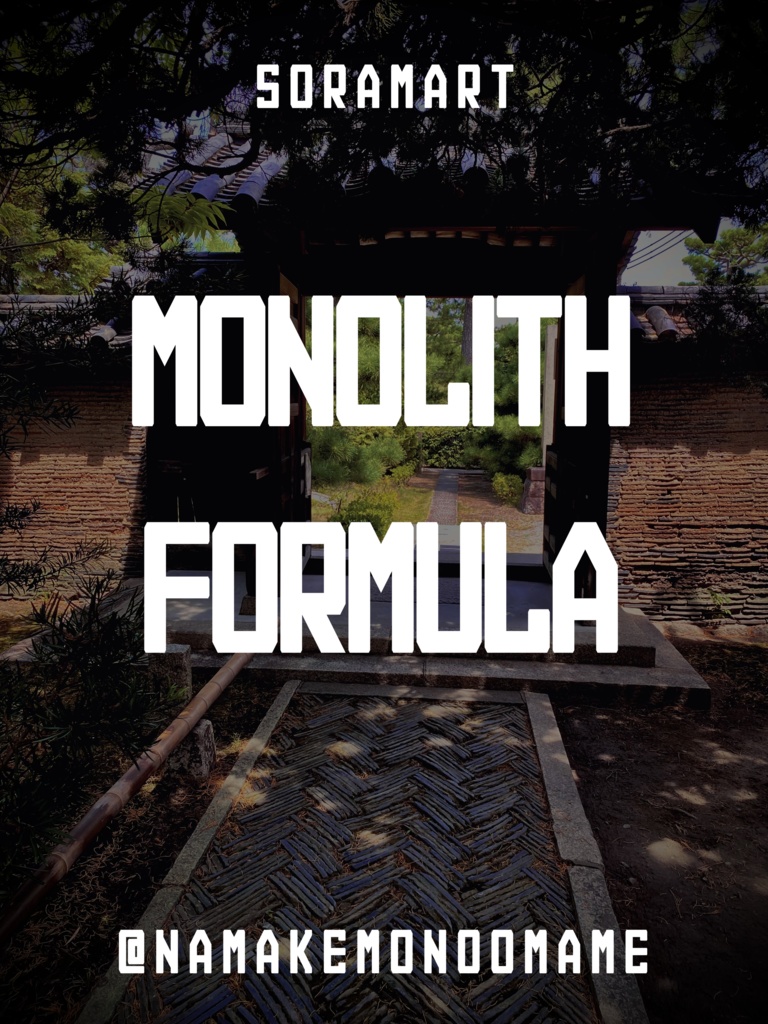
そらマートフォントデータ”Monolith Formula”Digital2,500 JPY加入购物车Buy a GiftAbout Giftシンプルスタイルの縦長フォント "Monolith Formula" です。 「TrueTypeフォントファイル」という形式です。 ダウンロードした後、Zipファイル内のデータをインストールしてお使いください。 このフォントは商用利用可となっております。 お客様の制作・創作活動のお役に立てれば幸いです。 ※使用上の注意事項などは、添付のReadmeをお読みください。そらマートVisit FANBOX!Fontsフォントデータ”Henge Edge Rock”そらマート200 JPYFontsフォントデータ”Henge Edge Tall”そらマート0 JPYFontsフォントデータ”Henge Edge”そらマート0 JPYFontsフォントデータ”Chisel Stroke Wide”そらマート2,500 JPYFontsフォントデータ”Chisel Stroke”そらマート0 JPYFontsフォントデータ”Crushed Can Serif Empty”そらマート2,500 JPYFontsフォントデータ”Crushed Can Serif Wide”そらマート2,500 JPYFontsフォントデータ”Crushed Can Serif”そらマート2,500 JPYFontsフォントデータ”Dolce Cube Tall”そらマート2,500 JPYFontsフォントデータ”Dolce Cube”そらマート2,500 JPYFontsフォントデータ”Eight-bit Quest Wide”そらマート2,500 JPYFontsフォントデータ”Eight-bit Quest”そらマート2,500 JPYFontsフォントデータ”Tonik Crate”そらマート2,500 JPYFontsフォントデータ”Vapor Sprout Edge”そらマート2,500 JPYFontsフォントデータ”Vapor Sprout Wide”そらマート2,500 JPYFontsフォントデータ”Vapor Sprout”そらマート2,500 JPYFontsフォントデータ”Star Shoot Ray”そらマート2,500 JPYFontsフォントデータ”Star Shoot Black Wide”そらマート2,500 JPYFontsフォントデータ”Star Shoot Black”そらマート2,500 JPYFontsフォントデータ”Mars Invader Balloon”そらマート2,500 JPY查看更多